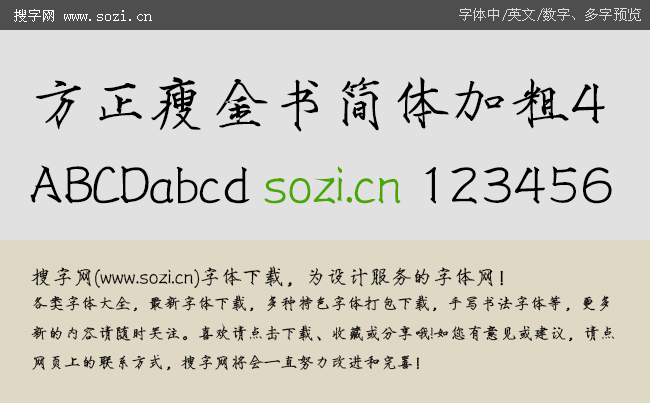
方正瘦金書體加粗4
搜字網(wǎng)提供一款方正瘦金書體加粗4手機中文字體下載,瘦金體為宋徽宗趙佶所創(chuàng),是書法史上的一項獨創(chuàng)。瘦金體運筆飄忽快捷,筆跡瘦勁,至瘦而不失其肉,轉(zhuǎn)折處可明顯見到藏鋒,露鋒等運轉(zhuǎn)提頓痕跡,是一種風格相當獨特的字體。適合喜歡書法的朋友下載哦。